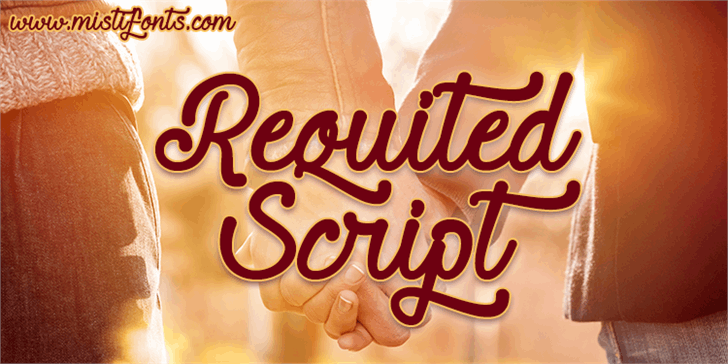
Aqui está uma descrição envolvente para a página de download da fonte ‘Requited Script Font’, em português do Brasil: Para quem busca trazer vida e graça aos seus designs digitais, a Misti’s Fonts apresenta o Requited Script Font. Este script é perfeito para adicionar um toque delicado e elegante a qualquer texto. Com suas curvas suaves e linhas finas, ele cria um estilo que transmite delicadeza sem perder seu poder de expressão. Ideal para títulos ou subtítulos em designs gráficos, publicações online ou materiais de impressão, o Requited Script font traz uma personalidade única à sua composição. Seja você designer gráfico, blogueiro ou criador de conteúdo digital, o Requited Script é a escolha certa para aqueles que desejam transmitir emoção e sofisticação em seus projetos. A Misti’s Fonts oferece essa fonte com todas as suas características completas, permitindo que você use seu estilo pessoal ao máximo. Não deixe de experimentar o Requited Script Font; ele vai transformar a forma como você apresenta texto nas mídias digitais!